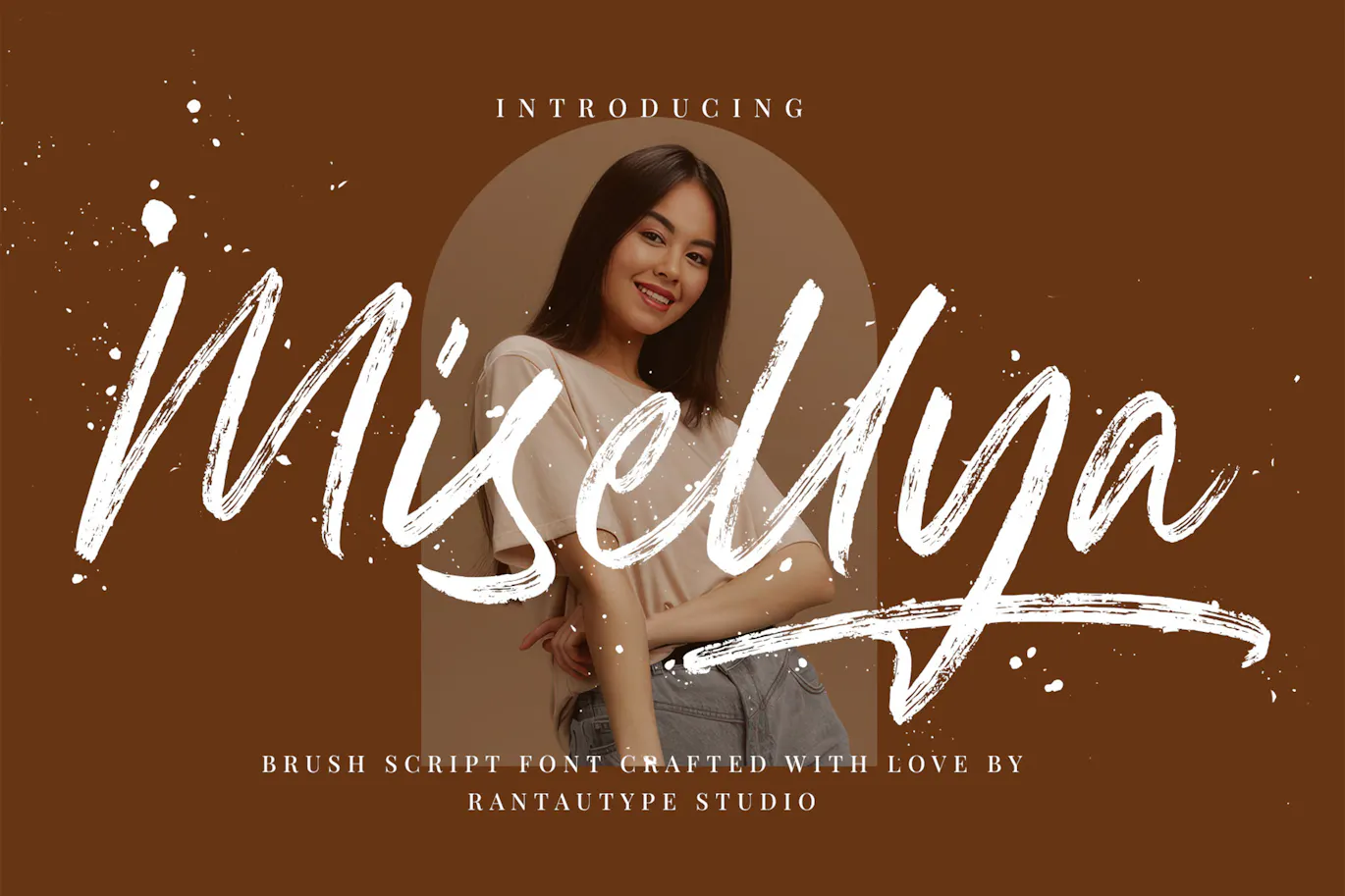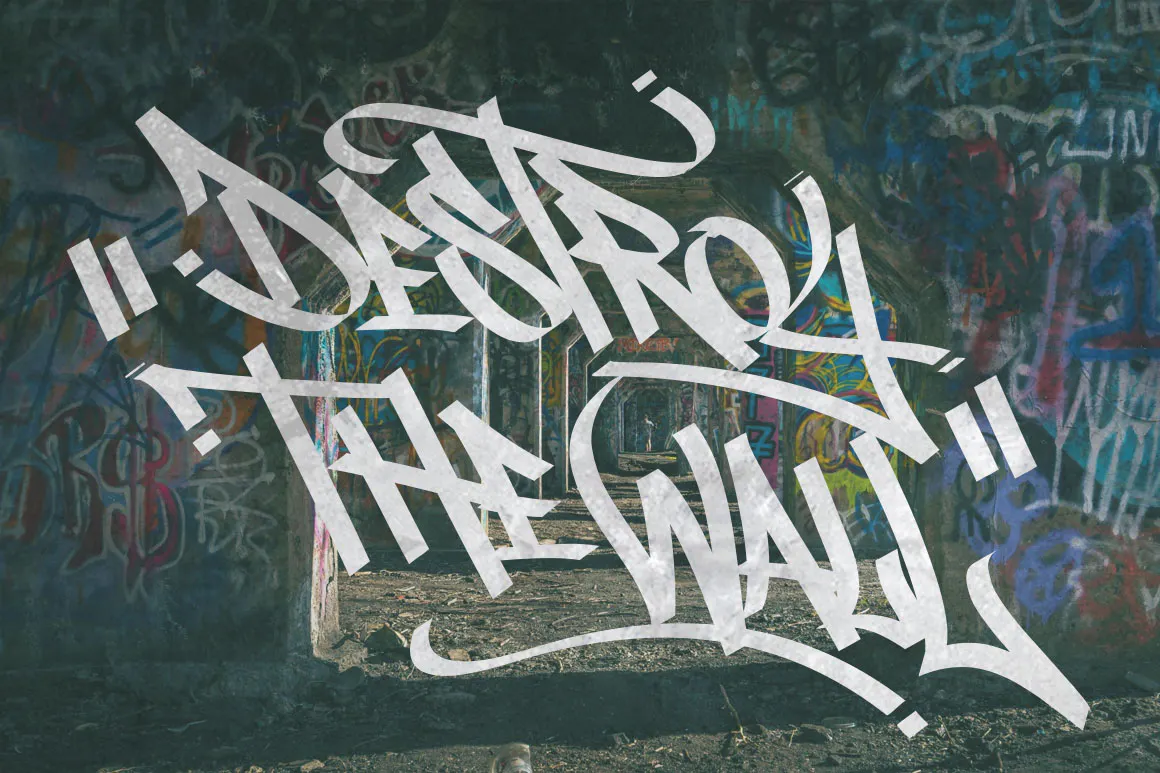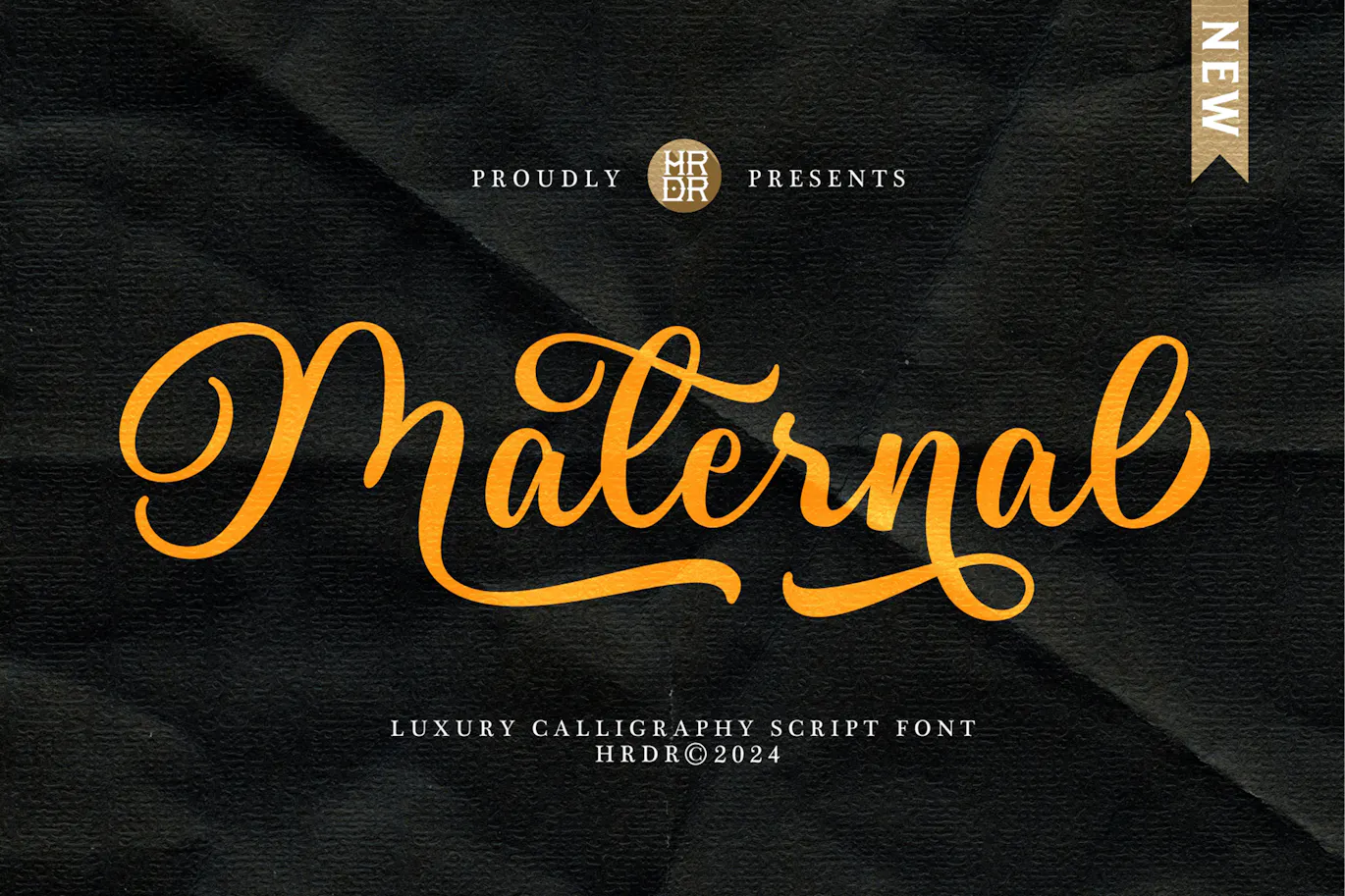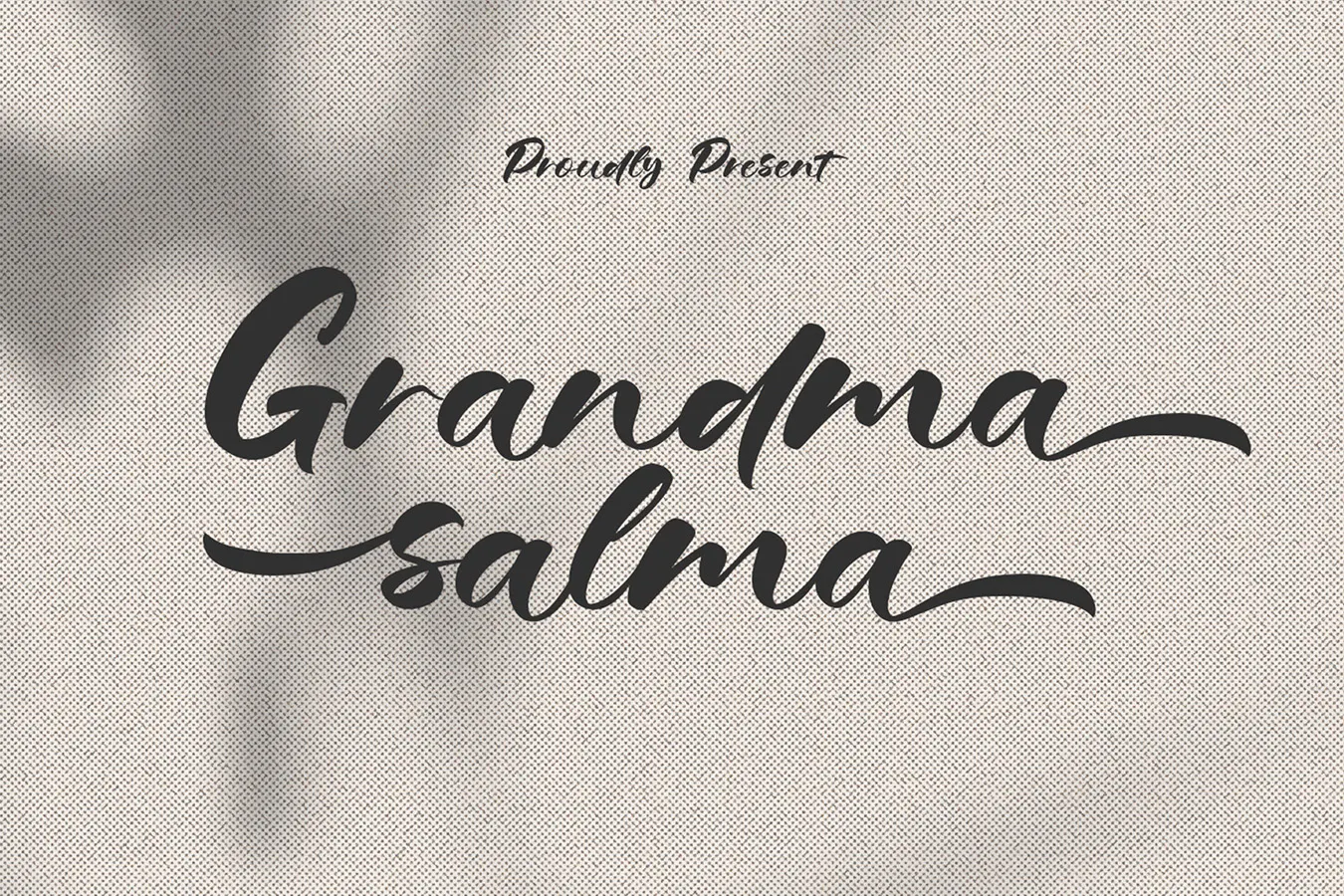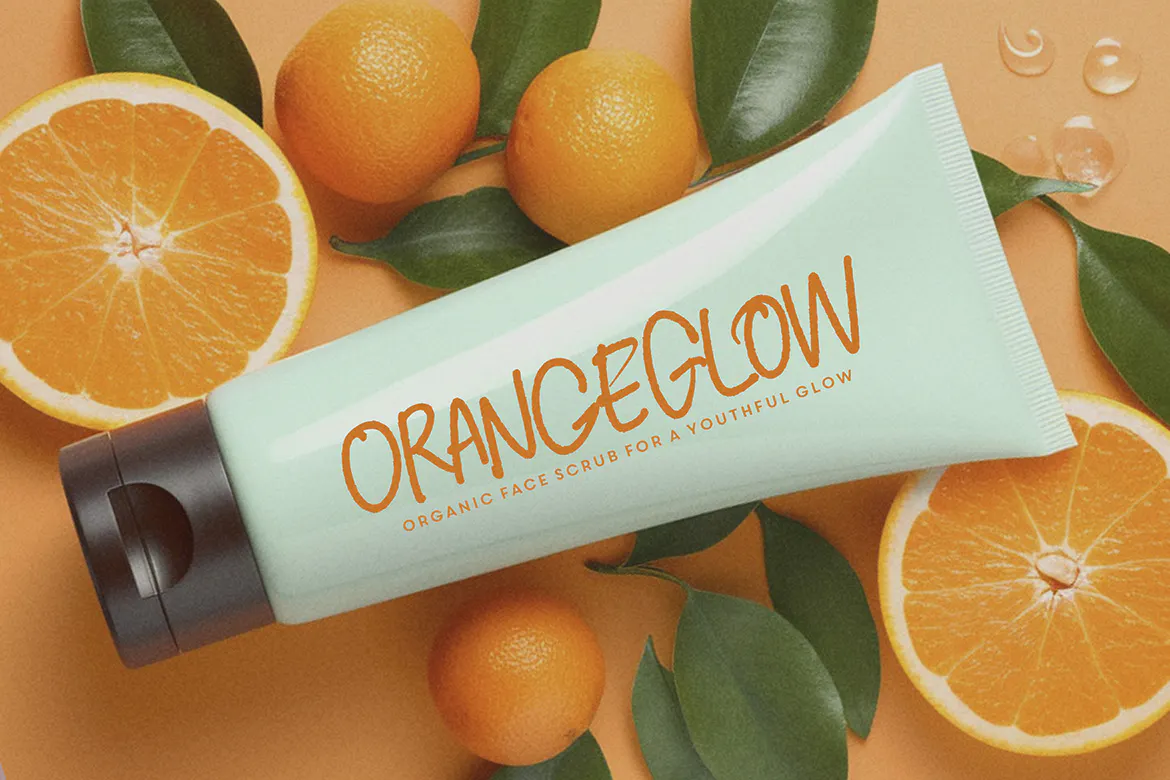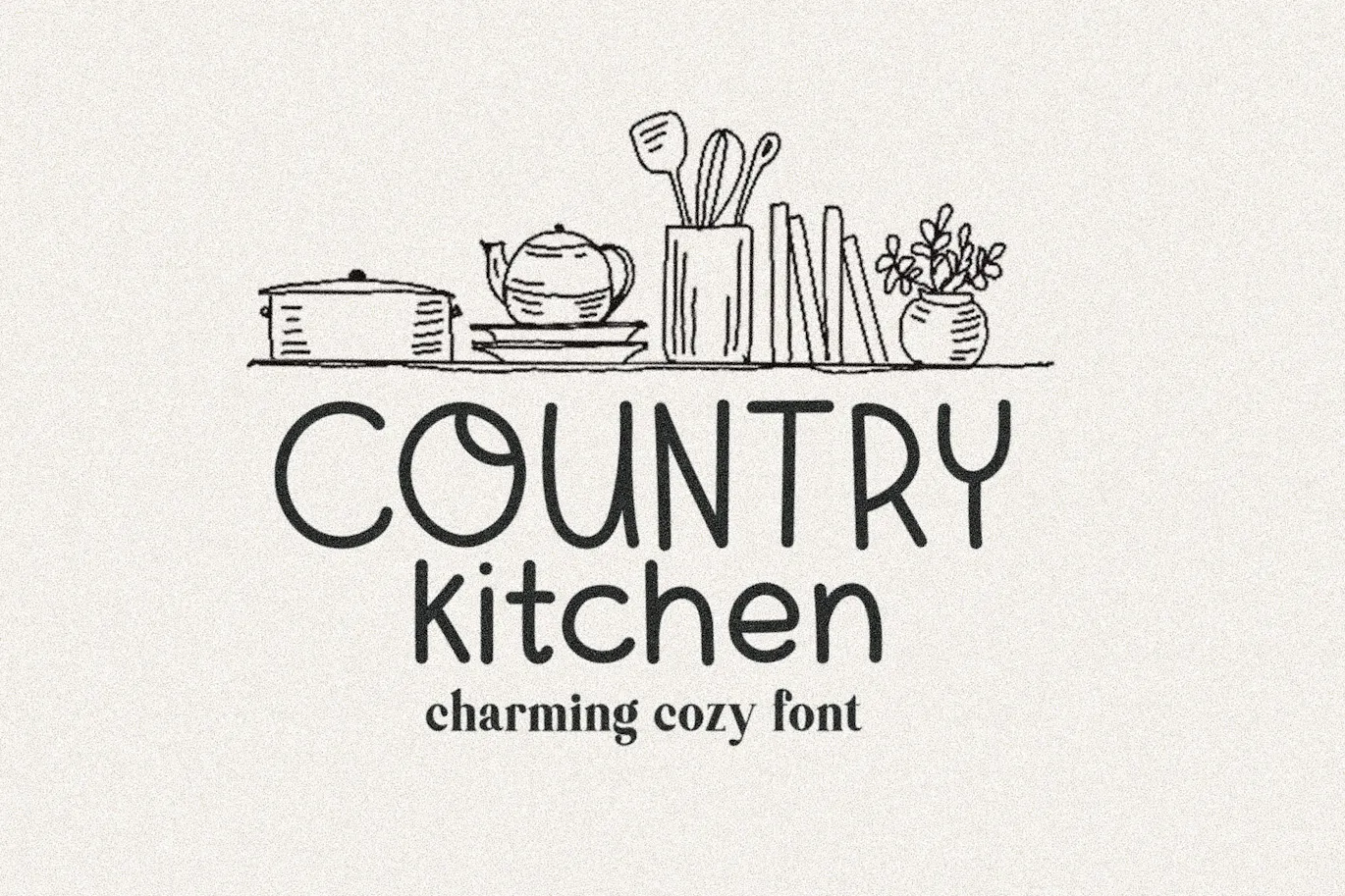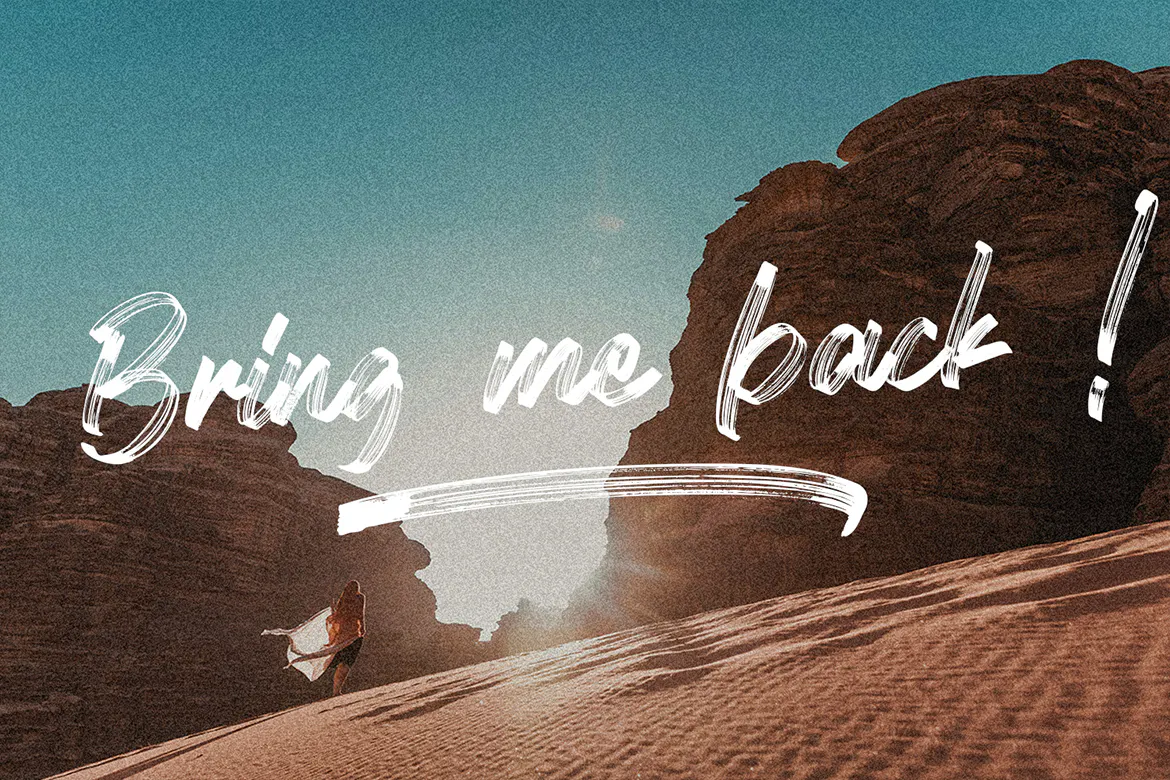
品牌推广包装设计的英文手写笔刷字体 – Misellya
Misellya是一款品牌推广包装设计的英文手写笔刷字体,具有明显的笔刷效果和自然的划痕。时尚的笔触使这款字体引人注目且用途广泛。Misellya 是任何创意、时尚、生活方式设计的完美选择,例如徽标、广告、摄影水印、文具、品牌项目、展示和杂志、邀请函、企业品牌、产品设计、标签、商业项目和许多其他项目需求手写的味道。字体格式有OTF、TTF、WOFF。- 42
手绘斜体效果的英文涂鸦字体 – Street Tag Vol1
Street Tag Vol 1是一款手绘斜体效果的英文涂鸦字体,灵感来自于雅加达市区的涂鸦标签,字体还提供矢量格式的一些奖励,您将获得轮廓字体、特殊字符(水滴、线条、另一个标签符号等)和嘻哈海报设计奖励,我还创建了特殊字母“G”、“Y”矢量库中还有“T”,因此您可以随意编辑路径,结合原始字体,您可以看到示例。字体格式有ttf。- 232
时尚品牌标志LOGO气质的英文手写字体 – Milaria Jams Handwritten Font.
Milaria Jams是一款英文手写字体,美丽、优雅、优雅、现代,该字体非常适合各种项目,例如签名、文具、徽标、婚礼、排版报价、杂志或书籍封面、网站标题、品牌、包装设计等。此外,与时尚相关的品牌或编辑设计展示了男性和女性的特质。字体格式有otf、ttf。- 470
现代而奢华的英文手写书法字体 – Maternal
Maternal是一款现代而奢华的英文手写书法字体,它非常适合品牌、婚礼请柬、摄影、霓虹灯、博主、徽标、贺卡、徽标、报价等。字体格式有OTF 和 TTF 。该字体的所有功能和特殊字符都包含在一个文件中。因此,可以使用支持 opentype 的程序或软件(如 Adobe Illustrator、Adobe Photosop 和 Adobe Indesign)轻松访问。- 580
邀请函的英文手写签名字体 – Grandma Salma
Grandma Salma是一款邀请函的英文手写签名字体,灵感来自祖母的温暖和爱。这种字体的性格亲切、温柔、充满温柔,就像祖母的拥抱总是让人感到安慰。字体非常适合婚礼请柬、生日贺卡和其他家庭活动,字体格式有TTF、OTF、WOFF。- 645
非常漂亮的英文手写签名字体 – Geppista
Geppista是一款英文手写签名字体,具有手工制作的 Signature 风格、装饰人物和舞蹈基线!贺卡、品牌材料、名片、引言、海报等邀请函非常漂亮!Geppista Signature 带有 200 多个字形。替代字符分为几个开放类型功能,例如花体、文体集、文体替代和连字。字体格式有otf、ttf。- 56
纹理斜体的英文有机手写字体 – Forever Darling
Forever Darling是一款纹理斜体的英文有机手写字体,这是一款引人注目的字体,设计看起来就像真实的有机手写体!在包装、社论、潜台词、引文和加载更多内容上使用这种漂亮的小字体。字体格式有OTF 和 TTF。- 45
迷人的朴素感英文手写字体 – Country Kitchen
Country Kitchen是一款迷人的朴素感英文手写字体,非常适合创建贴纸、报价、印刷品、cricut 项目、热升华设计和 svg 文件。字体格式有 TTF、OTF。 字体兼容: Adobe Illustrator Adobe Photoshop Procreate Photopea Cricut Design Space Canva Pro version- 76
笔刷效果英文手写装饰字体 – Millionth Dream
Millionth Dream,一款纹理画笔笔刷效果的英文手写装饰字体, 纹理笔迹字体将笔迹特征与纹理元素相结合,形成一种散发着真实、温暖和深度的字体。 以下是其主要功能和优点的详细介绍: -画笔脚本风格:纹理画笔脚本字体的灵感来自于用毛笔或画笔手工刻字。它们具有流畅的笔触、不同的厚度和毛笔字的不规则特征,赋予它们自然和有机的外观。 -纹理元素:与干净光滑的笔刷脚本字体不同,纹理笔刷脚本字体将粗糙…- 47
自然纹理的英文手写连体签名字体 – Rizanico
今天分享的是是一款自然纹理的英文手写连体签名字体:Rizanico,字体将在您的所有设计、邀请函、海报设计、书籍设计、品牌材料、徽标和所有项目设计其他方面看起来华丽。字体包含标准字符、小写、大写、替代字符、数字、标点符号、连字和国际字形。您将收到 OTF、TTF 文件和 WEB FONT。- 70